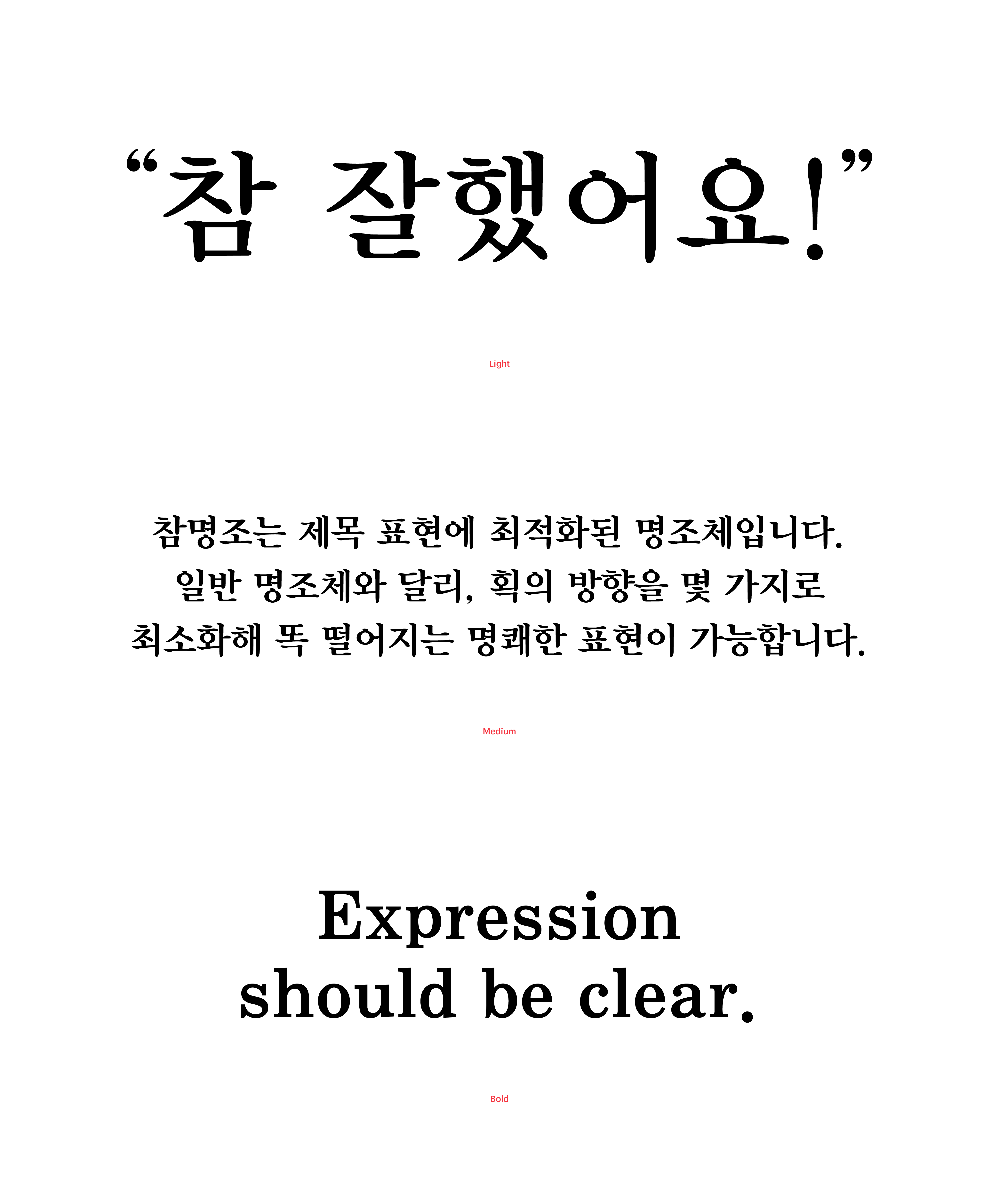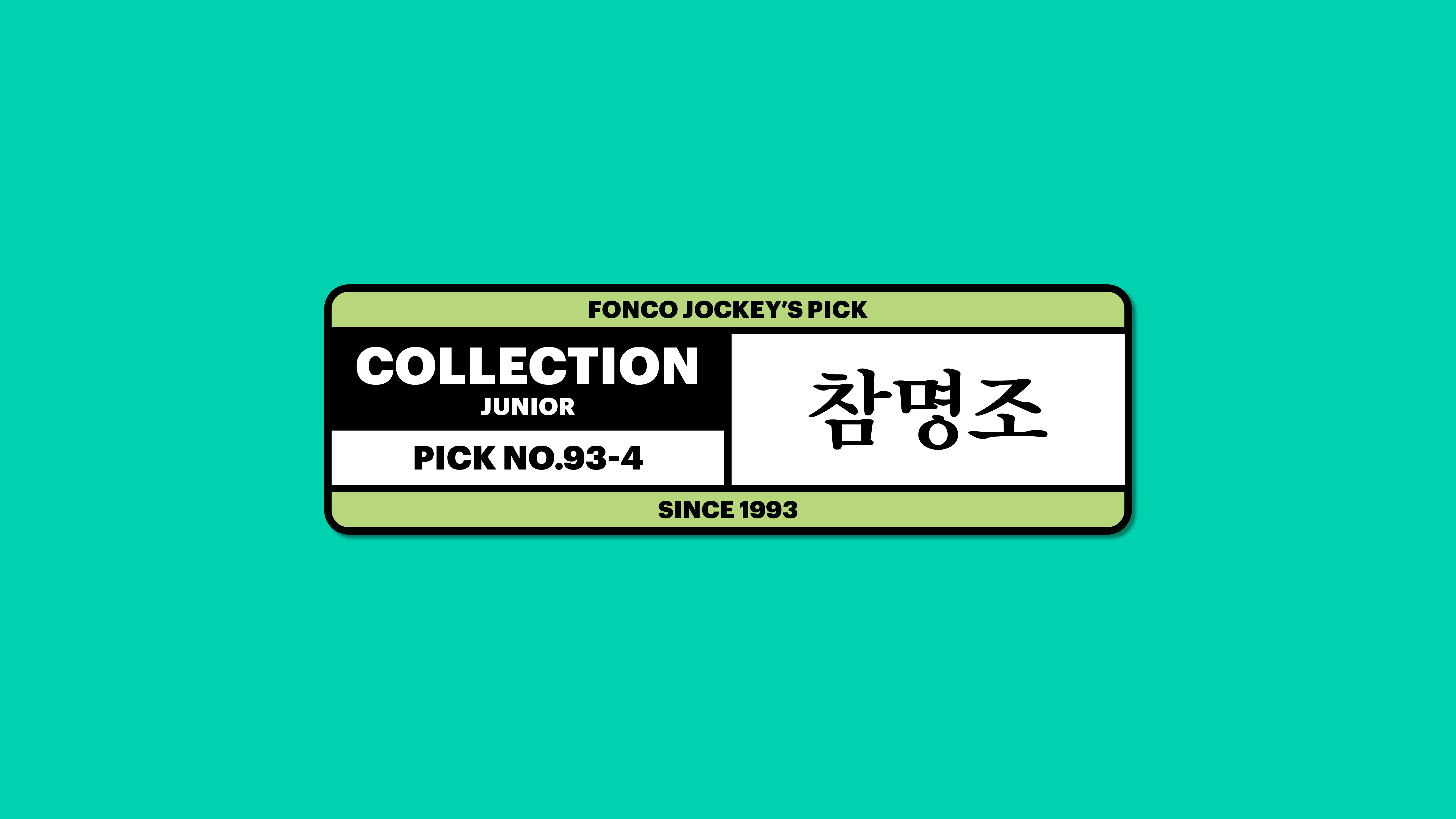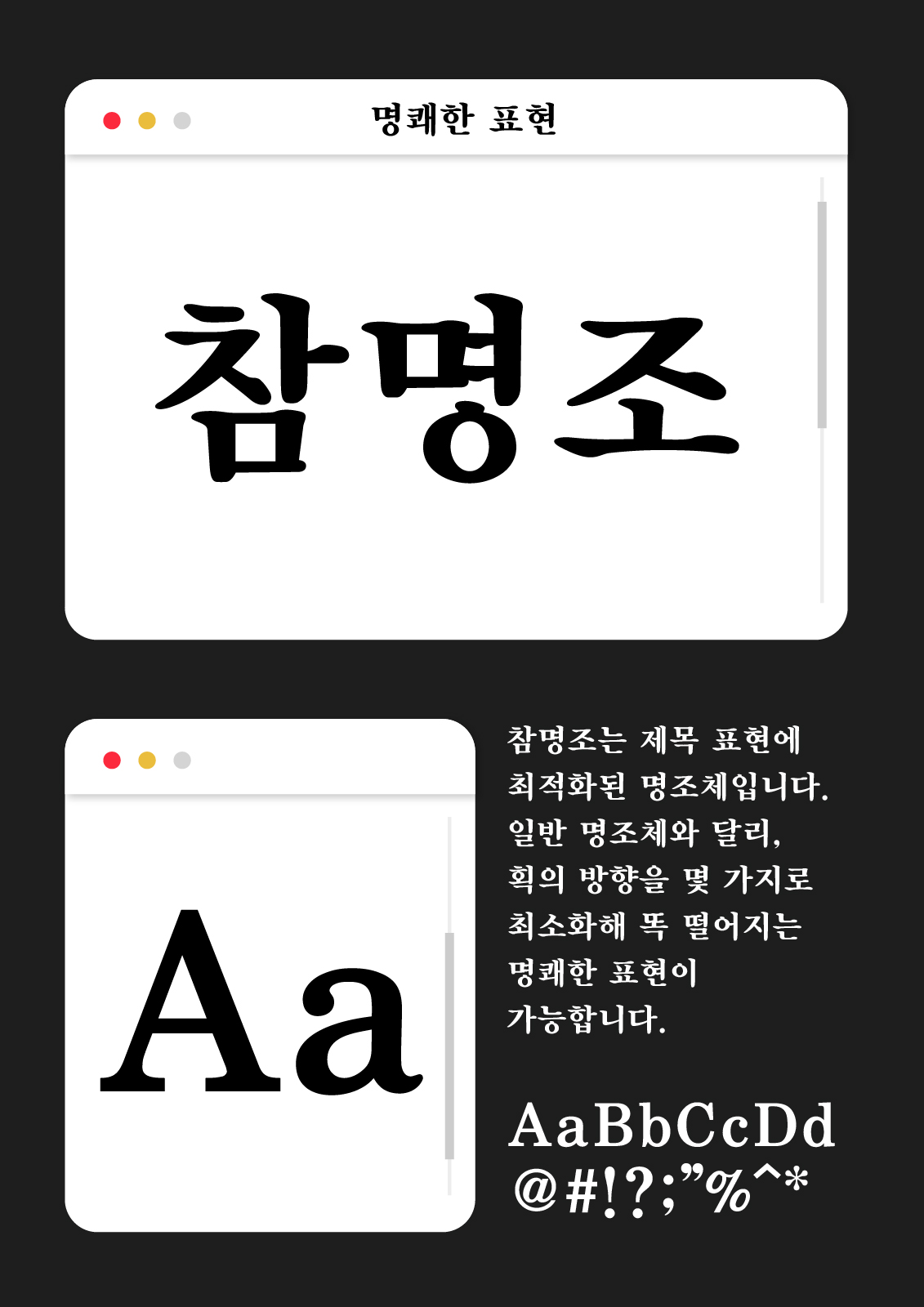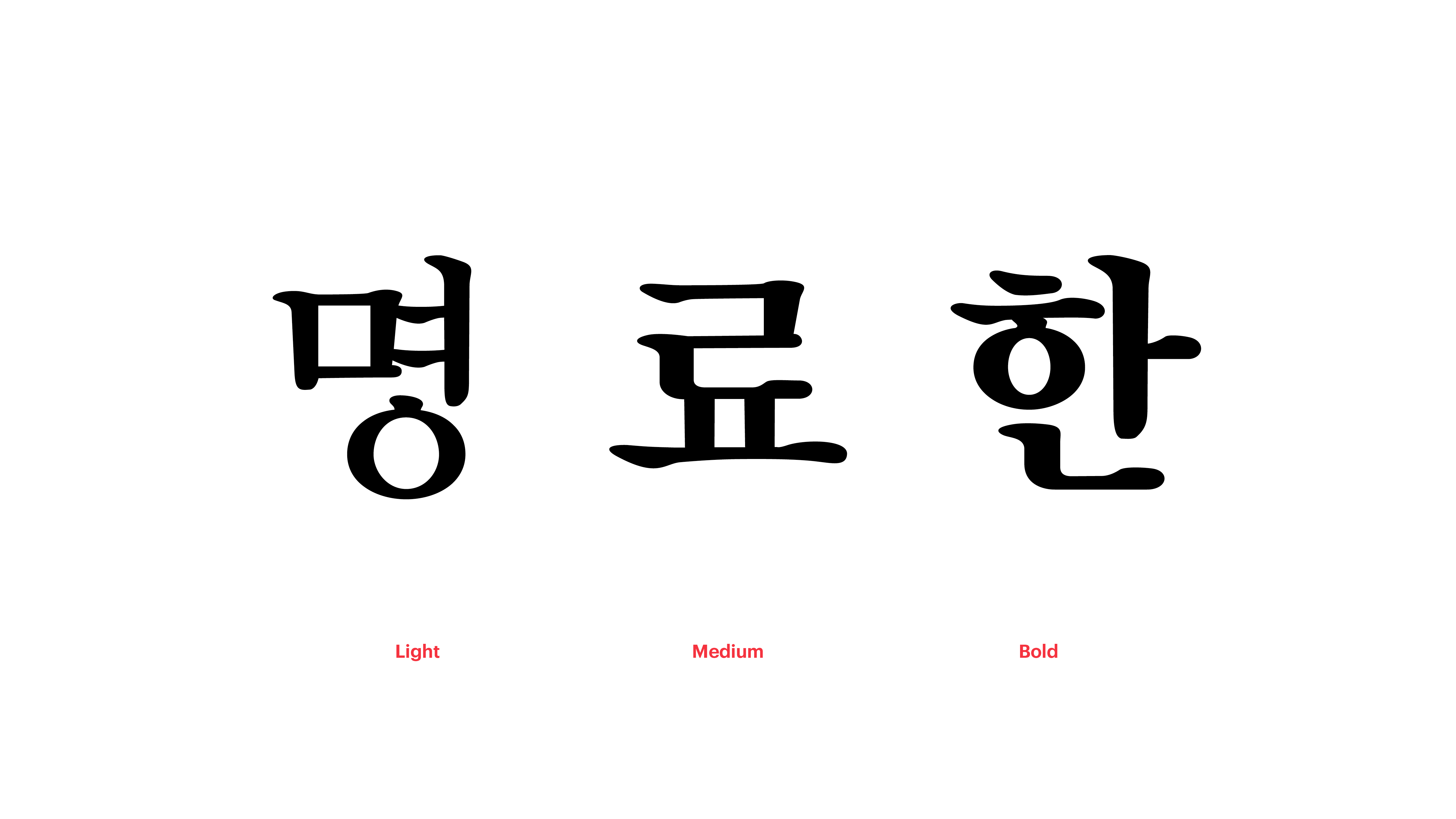
1990-1994
참명조는 제목 표현에 최적화된 명조체입니다. 일반 명조체와 달리, 획의 방향을 몇 가지로 최소화해 똑 떨어지는 명쾌한 표현이 가능합니다. 그뿐인가요? 받침닿자*의 위치를 조정하고 닿자**의 크기를 최대한 큼직하게 표현하여, 같은 급수의 기존 폰트보다 시각적으로 눈에 띄는 효과도 톡톡히 누릴 수 있답니다. *받침닿자 : 끝소리를 나타내는 글자. 종성, 받침을 시각적으로 일컫는 표현. **닿자 : 한글 ‘닿소리 글자’의 줄임말, 자음을 시각적으로 일컫는 표현.
Yoon 참명조